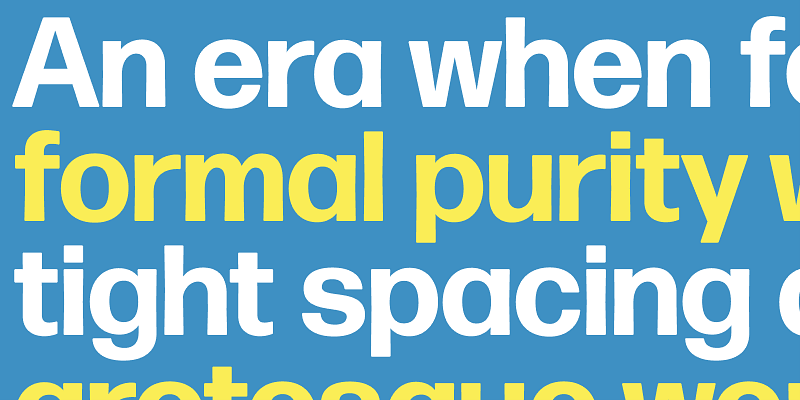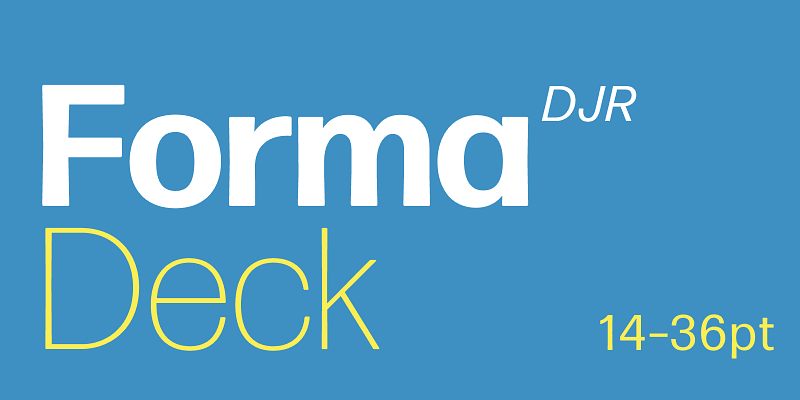
Forma DJR es el resurgimiento de la neo-grotesque Aldo Novarese de finales de mediados de siglo de la casa tipográfica italiana Nebiolo. En cooperación con Roger Black e Indra Kupferschmid, David Jonathan Ross estudió la letra de metal original e interpretó el diseño como una gran familia con tamaños ópticos, esquinas redondeadas y astas afiladas. La gama de pesos se llevó más adelante a los extremos Hairline y Black y se reimaginó como espacio de diseño variable, con aportaciones de Ruggero Magrì.